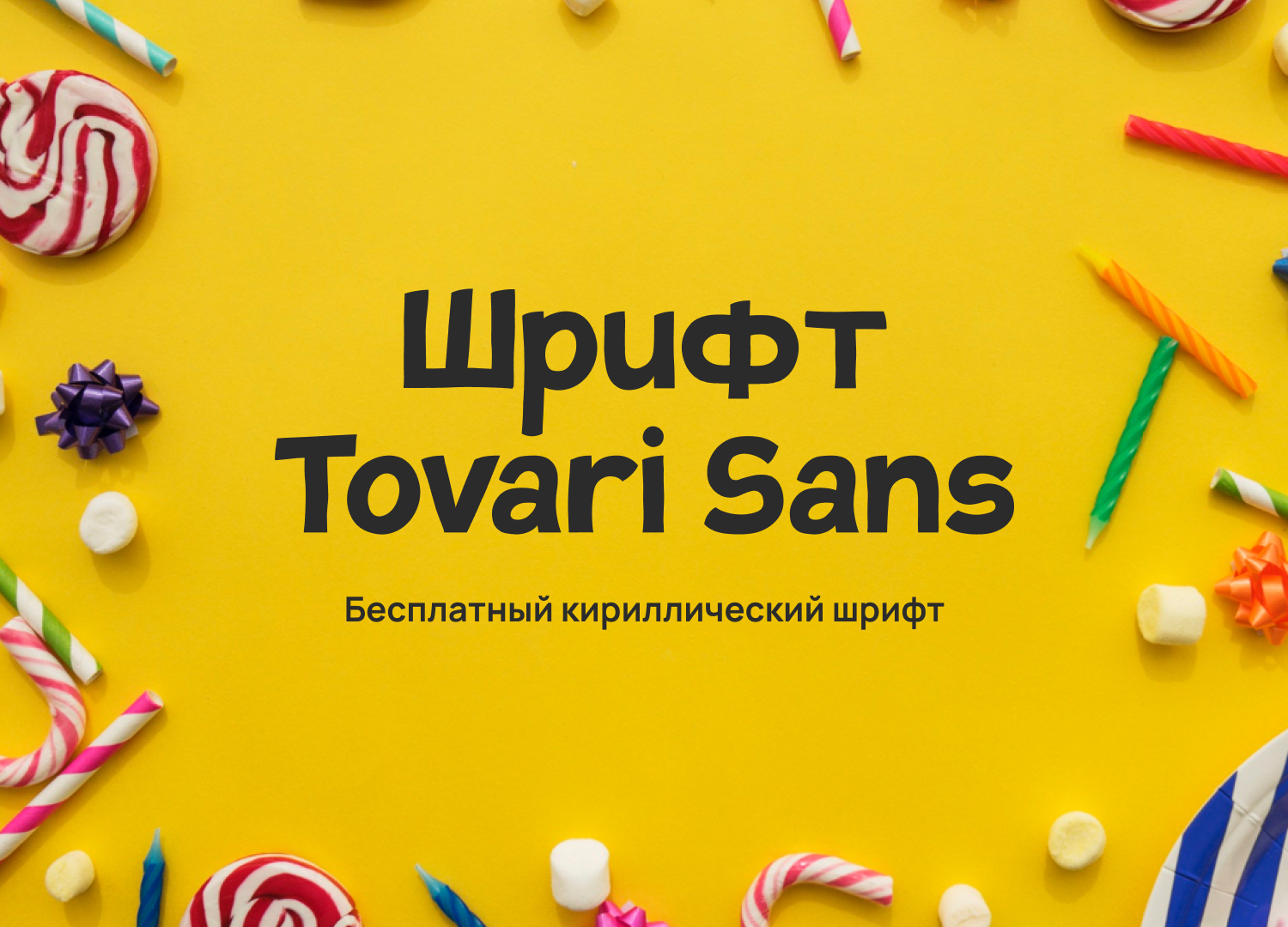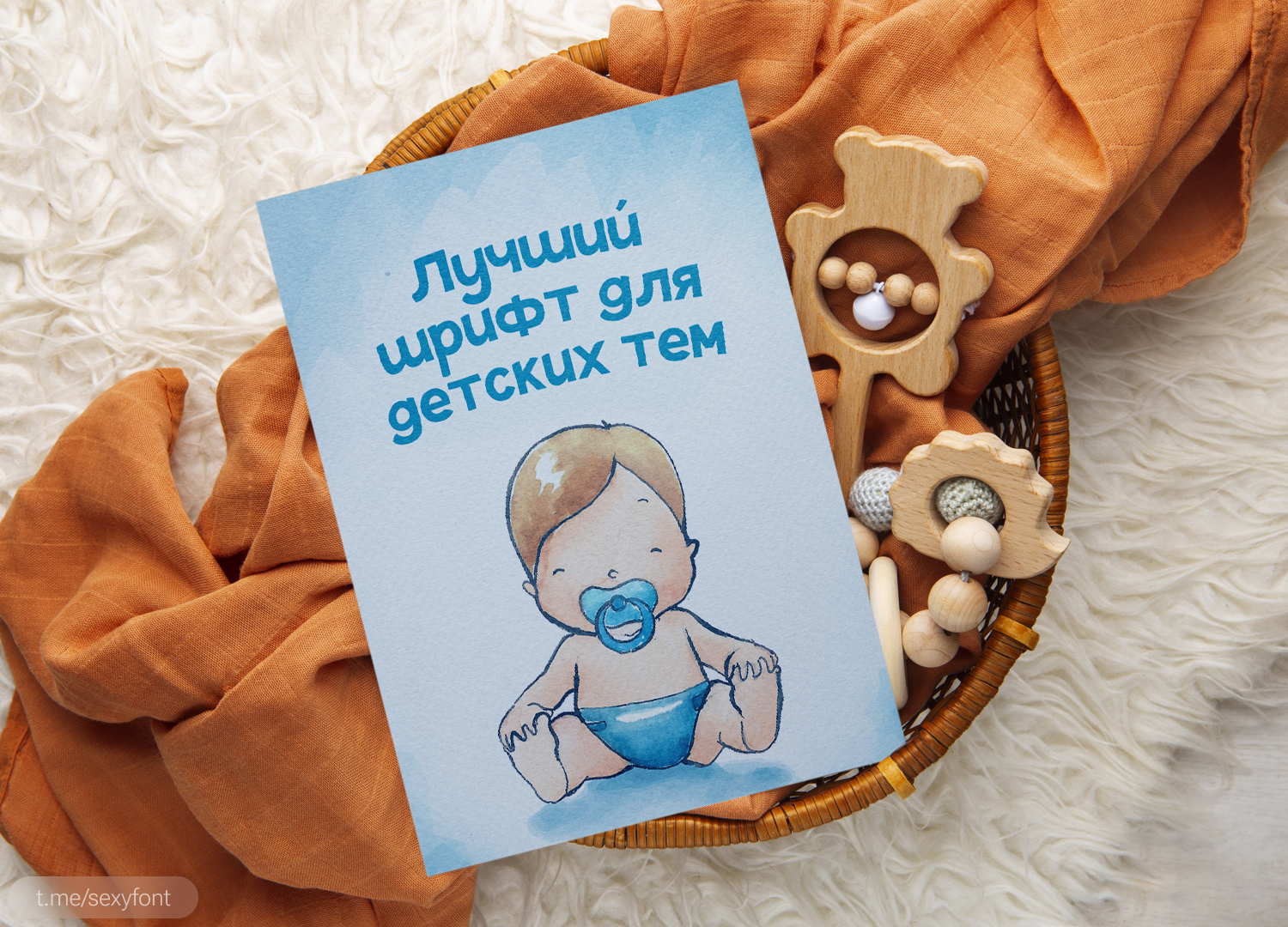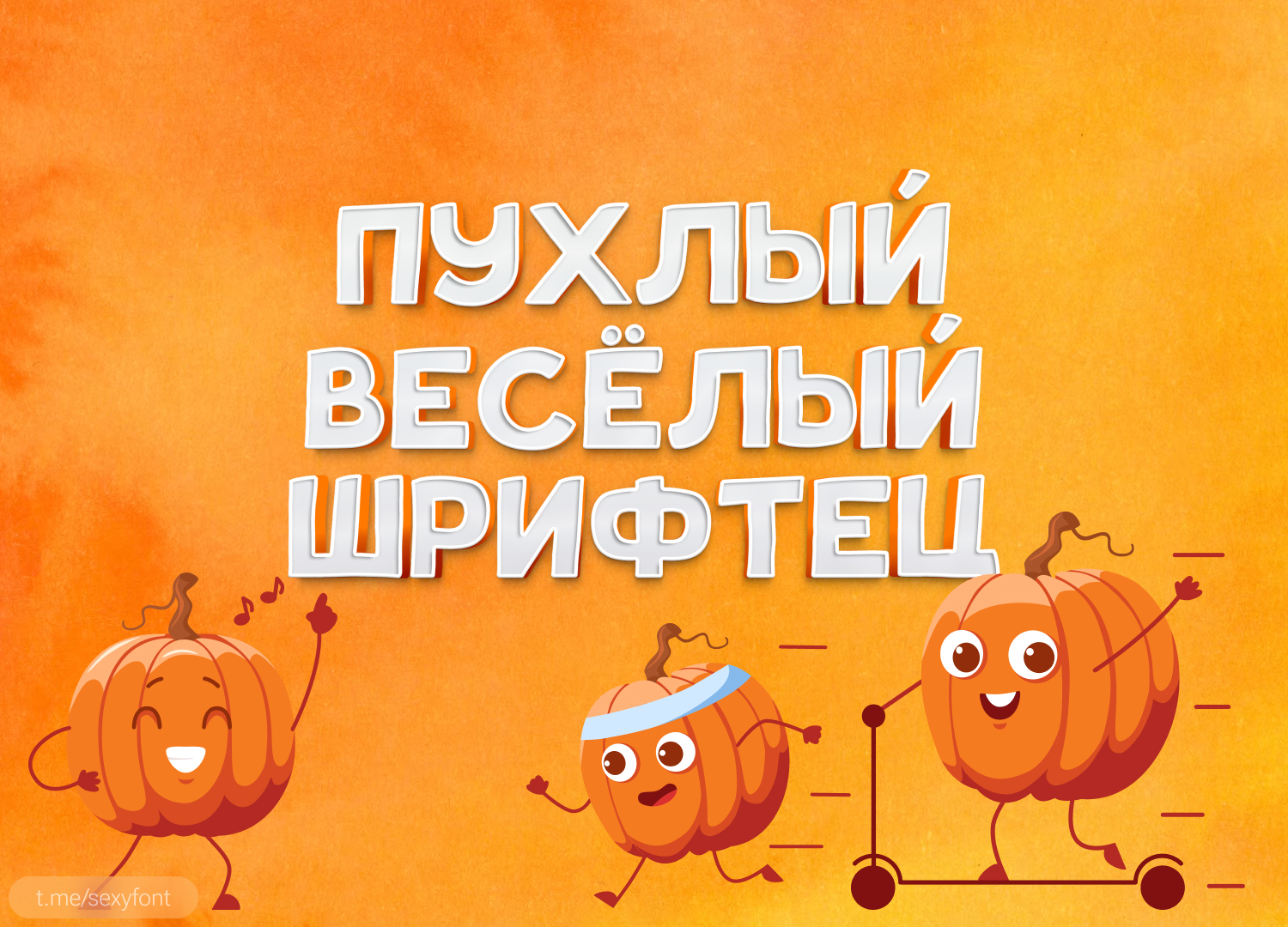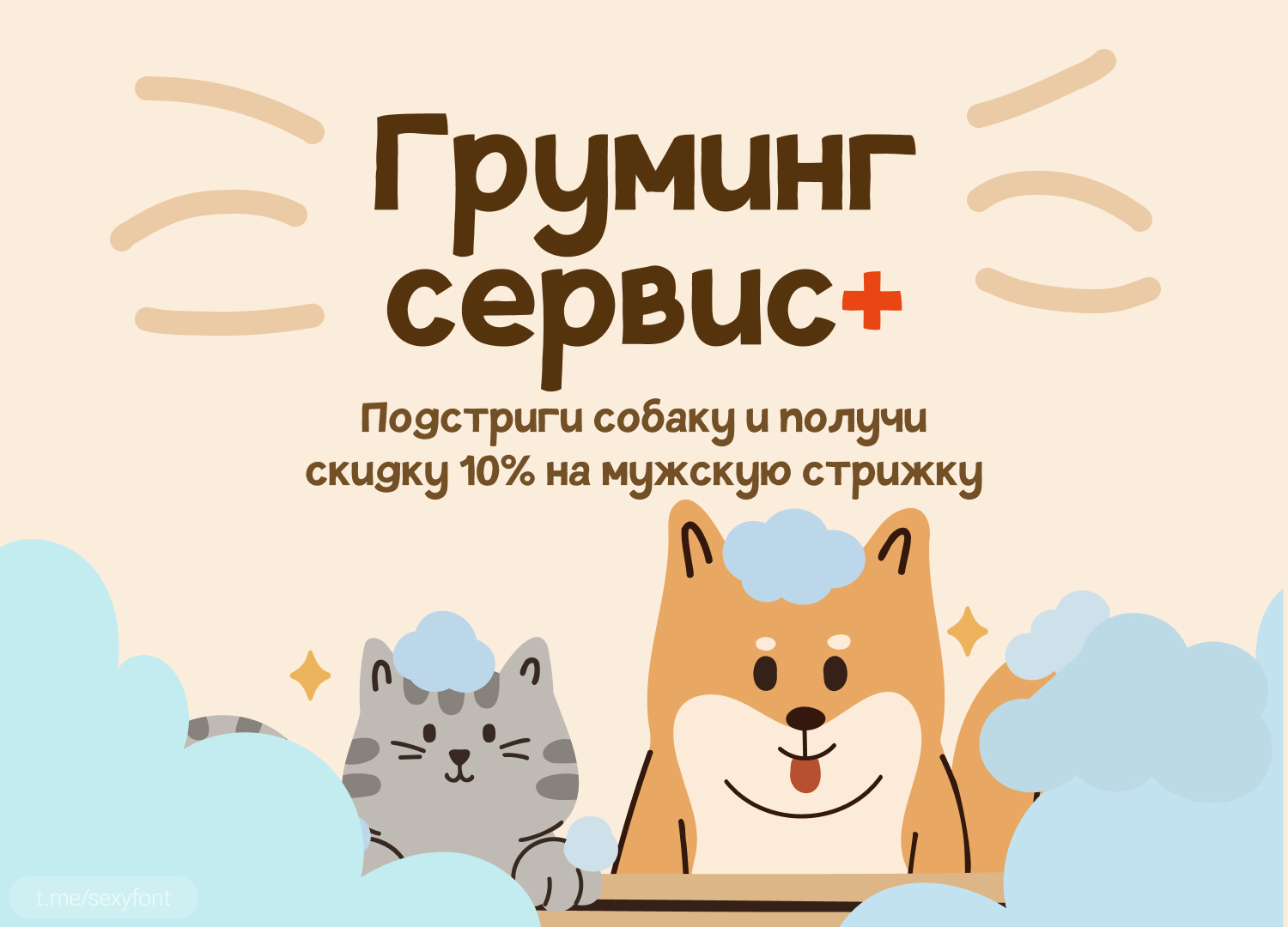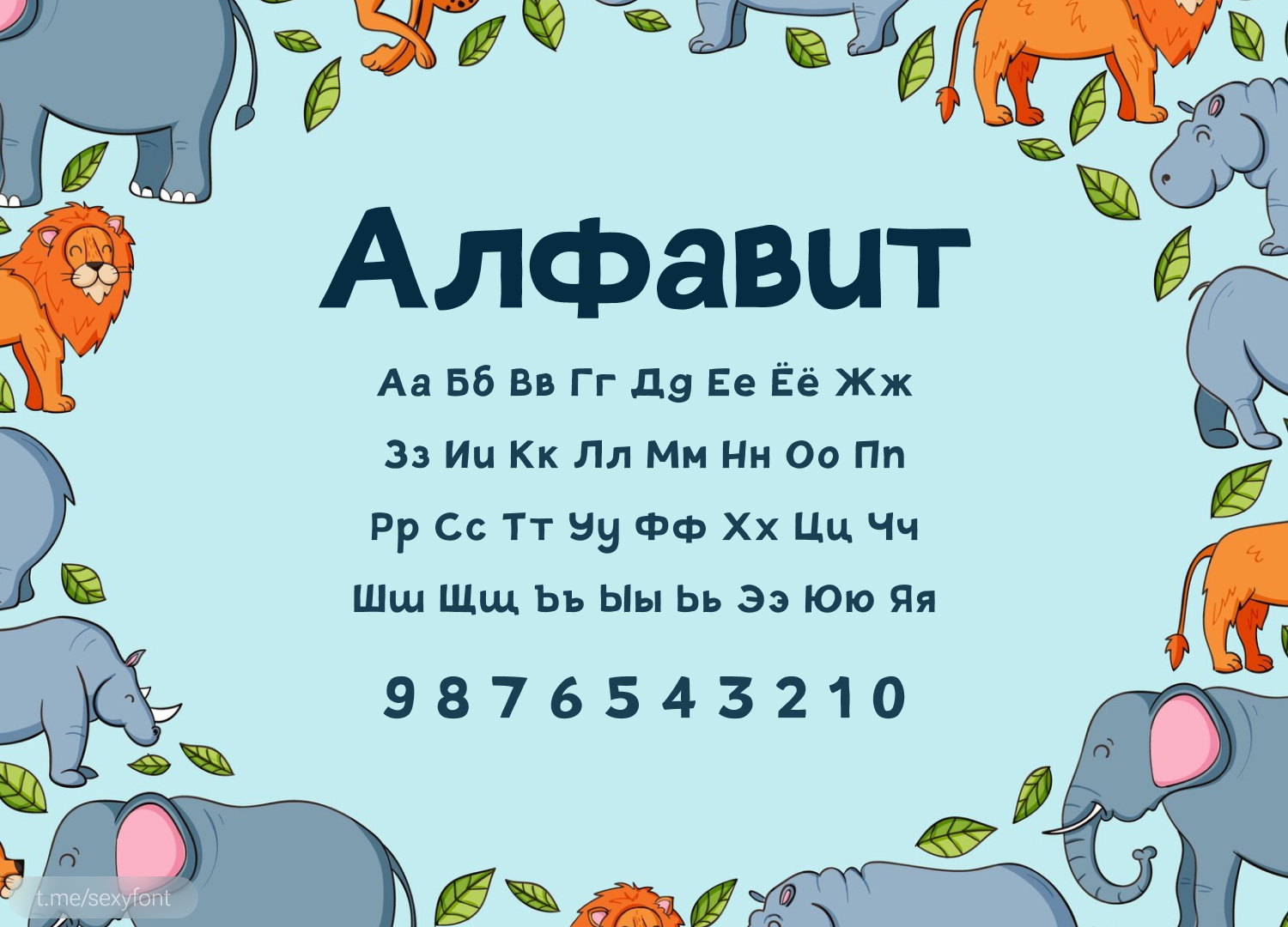
Бесплатный шрифт Tovari Sans. Кириллица
Пухлый, как бабушкин пирожок шрифтец. Идеально для детских тематик, праздников, фуд и всего такого. Решать уже вам. Моё дело в презентацию наглядную завернуть и тебе показать)